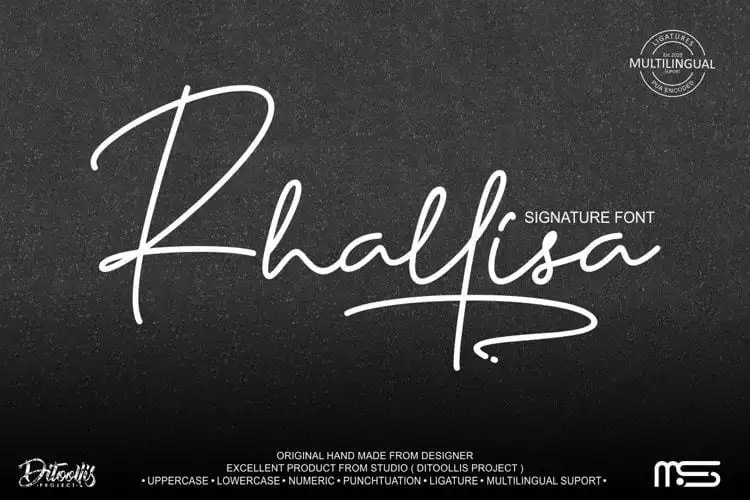
Rhallisa Handwritten Font – Download Grátis
A Rhallisa Handwritten Font é uma elegante fonte de script inspirada nas assinaturas que tornam a escrita não apenas única, mas também divertida e inovadora. Este design criado pelo Ditoollis Project se destaca na categoria das fontes manuscritas modernas, sendo perfeitamente adaptável para diversas aplicações gráficas. Com seu carácter minimalista e versátil, esta fonte é ideal para variados projetos como cartões de visita, logomarcas, capas, quadrinhos e convites casamento, tornando-a uma opção inteligente para designers atentos que desejam dar um toque personalizado e único aos seus projetos.